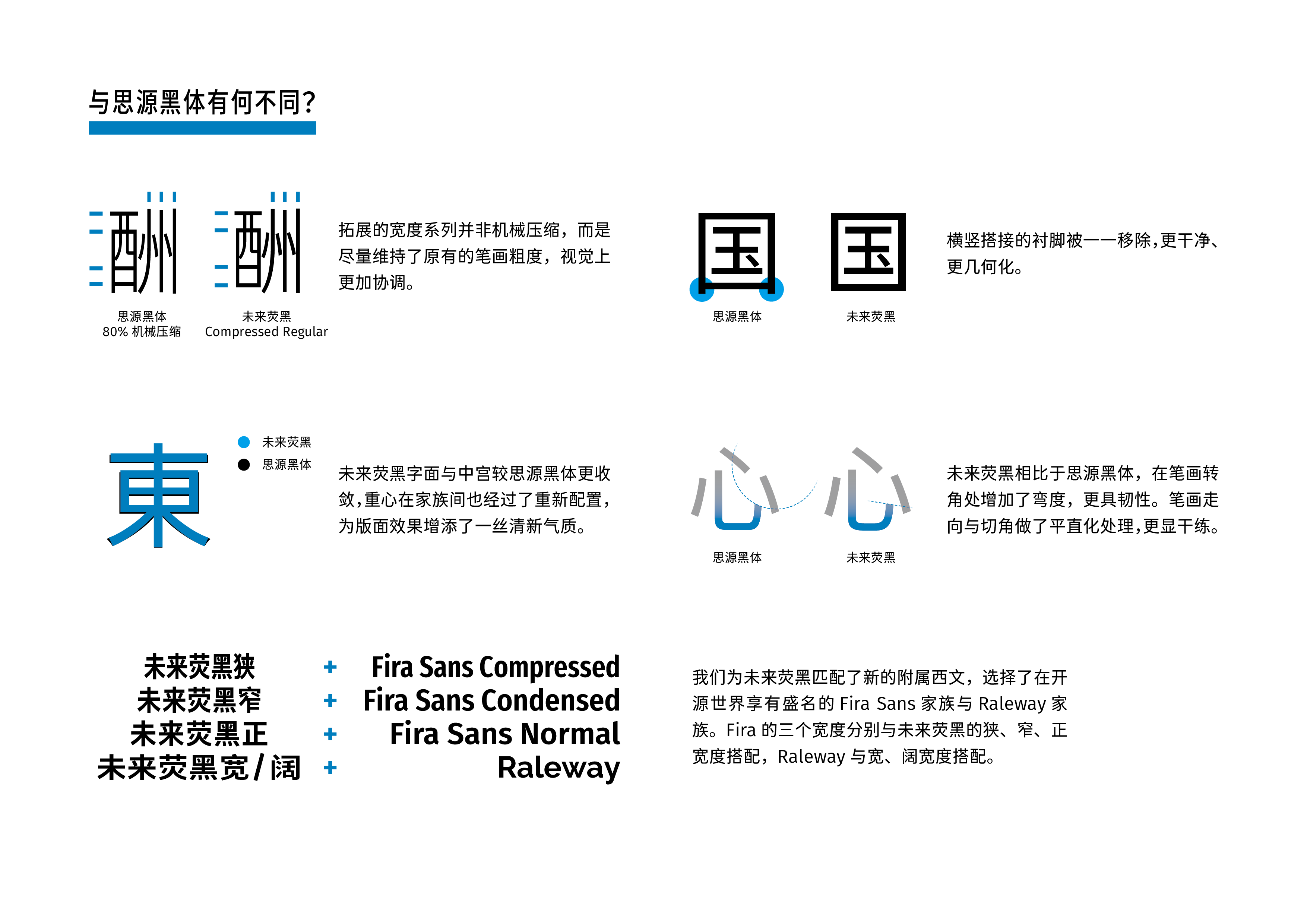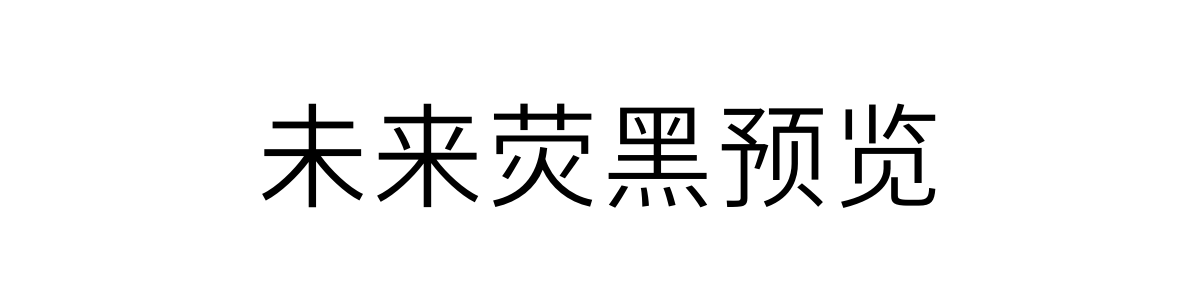
未来荧黑
未来荧黑(Glow Sans)是基于思源黑体Fira SansRaleway 做的开源字体,在原有 7 个字重的基础上扩展到 9 种,还做了标准、窄、宽三种宽度,整个家族一共有 44 款字体。
支持简繁中文和日文,制作方式也很特别,不是用传统字体软件,而是靠网页可视化参数工具加算法直接生成字形。
字体风格
未来荧黑保留了思源黑体的清晰结构,同时整体更紧凑精致,中宫收得更紧。笔画简化得很干净,没有多余装饰,线条偏平直几何感。整体轻盈通透,有数字界面那种清爽锐利的质感,和传统黑体的厚重感完全不一样,现代感很足。